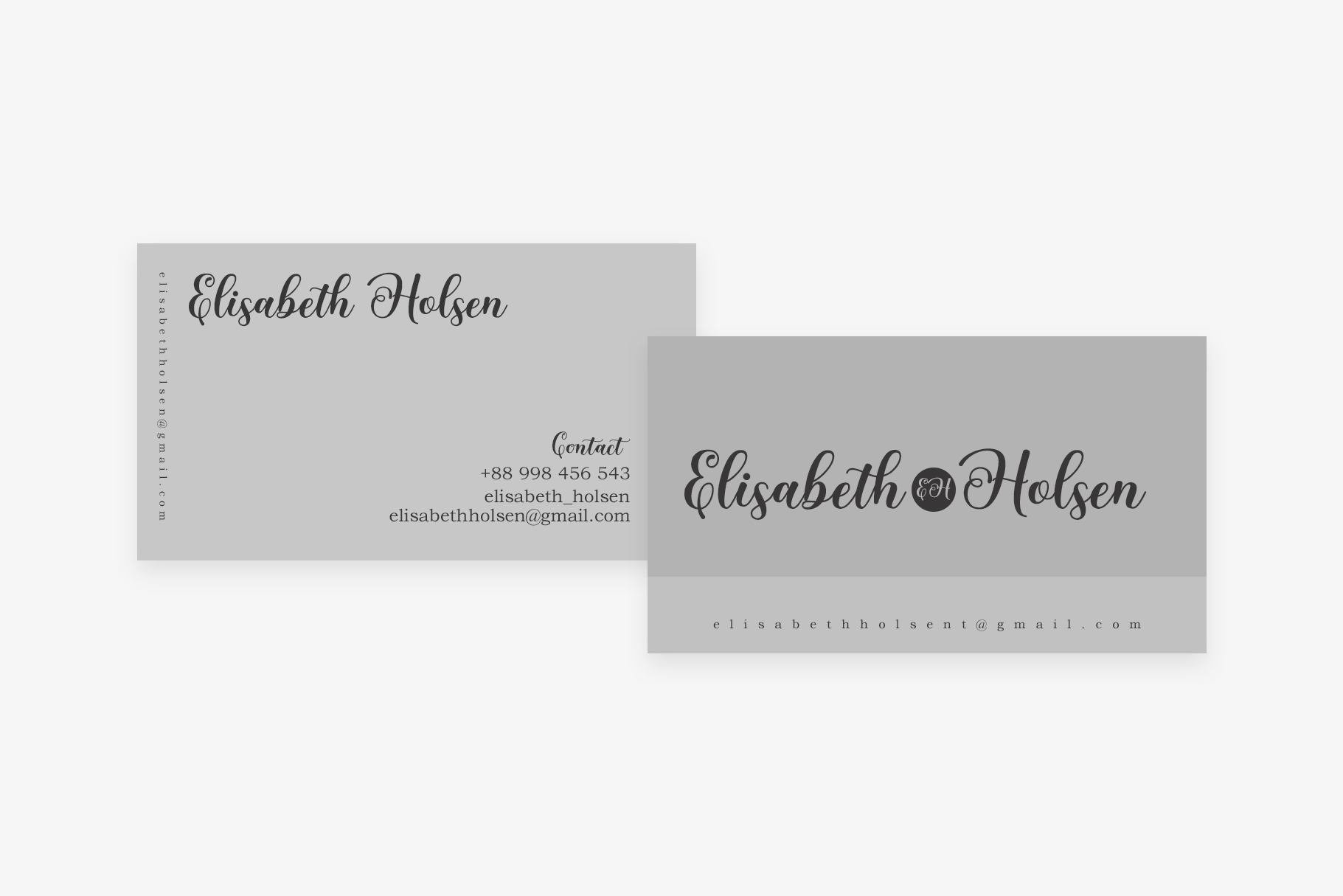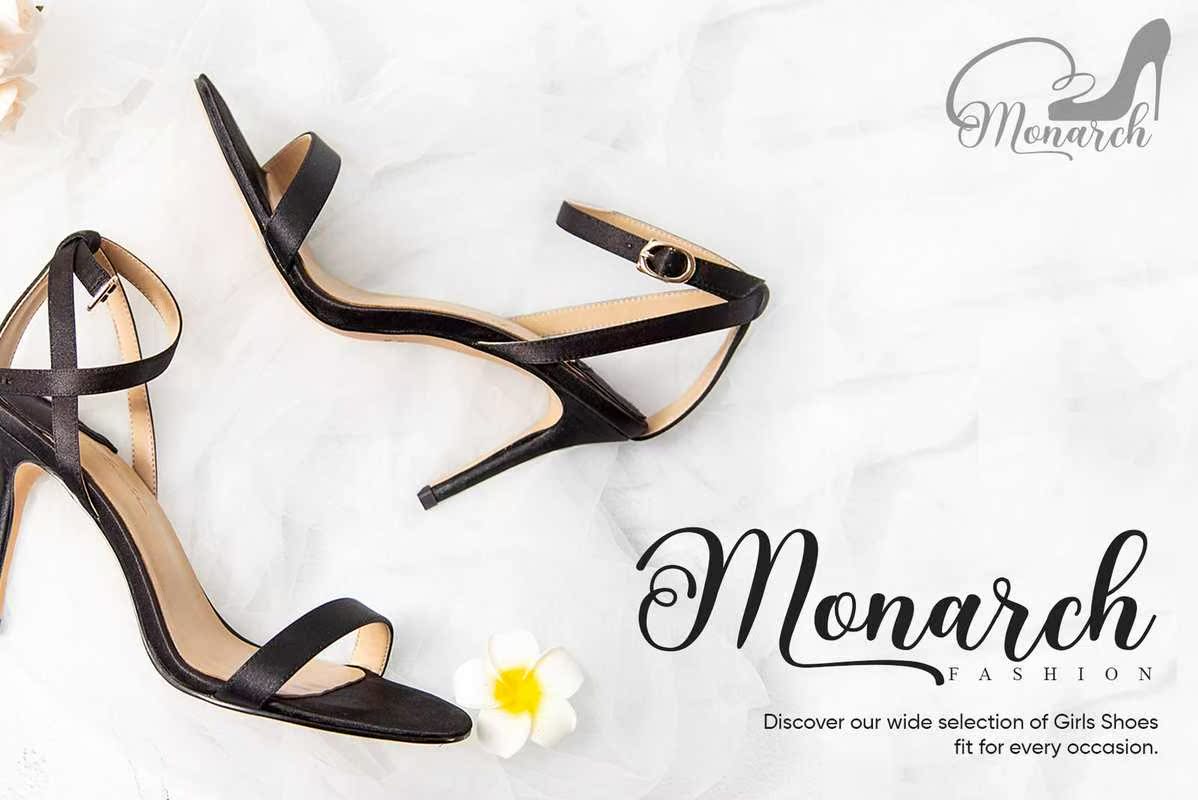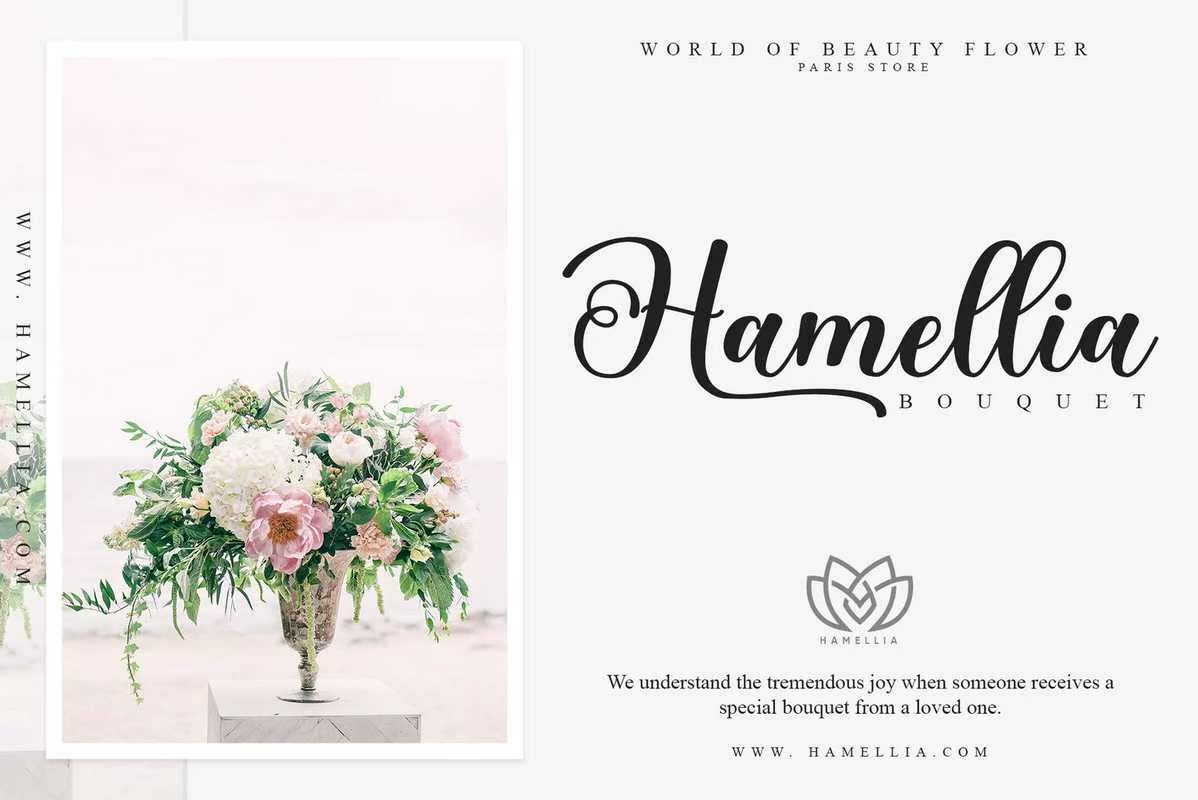
Love Amsterdam Signature Peface.适合您的项目的文字和数字集合非常适合于标识、品牌设计、标识设计、数字刻字艺术、T恤/服装、海报、杂志、标志、广告设计和任何设计需求。Love Amsterdam Signature Peface.适合您的项目的文字和数字集合非常适合于标识、品牌设计,标志设计、数字文字艺术、T恤/服装、海报、杂志、标志、广告设计和任何设计需求。